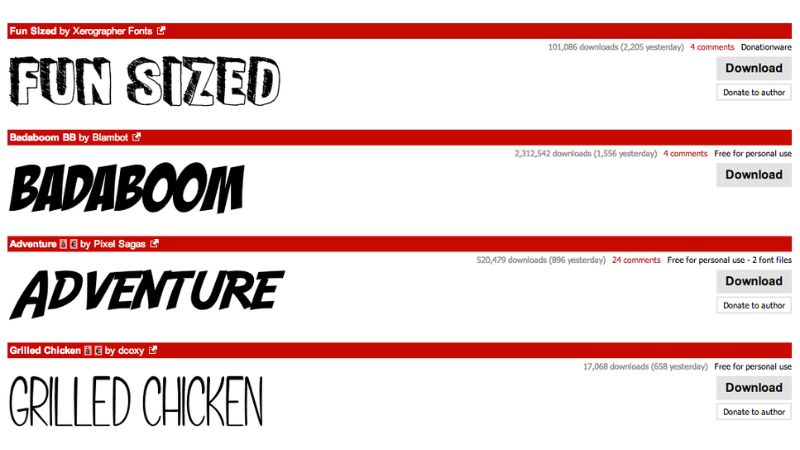
Trong thế giới của thiết kế và sáng tạo, font chữ không chỉ đơn thuần là những con chữ. Chúng là linh hồn của văn bản. Chúng có khả năng truyền tải cảm xúc, định hình phong cách và tạo ra một ấn tượng thị giác mạnh mẽ. Một font chữ được lựa chọn đúng đắn có thể biến một văn bản bình thường trở nên sang trọng. Nó cũng có thể làm cho một thiết kế trở nên vui nhộn hoặc chuyên nghiệp hơn. Tuy nhiên, việc tìm kiếm những font chữ đẹp và miễn phí không phải lúc nào cũng dễ dàng. Rất may mắn, có một “thiên đường” dành cho những người yêu thích font chữ. Đó chính là trang web DaFont. Bài viết này sẽ là một cẩm nang toàn diện. Chúng tôi sẽ hướng dẫn bạn mọi thứ về DaFont, từ cách tìm kiếm, tải về cho đến cài đặt và sử dụng.
DaFont là gì? Khám phá “Thiên đường” font chữ miễn phí
Trước khi bắt đầu tải về, việc hiểu rõ về font chữ và trang web DaFont sẽ giúp bạn có một cái nhìn tổng quan và sử dụng tài nguyên này hiệu quả hơn.
Font chữ là gì? “Trang phục” quyết định linh hồn của văn bản
Hãy tưởng tượng các con chữ giống như những người mẫu. Font chữ chính là những bộ trang phục mà họ khoác lên mình. Cùng một nội dung văn bản, nhưng với những font chữ khác nhau, nó sẽ mang lại những cảm giác hoàn toàn khác biệt. Một font chữ chân phương (serif) như Times New Roman sẽ tạo cảm giác trang trọng và cổ điển. Một font chữ không chân (sans-serif) như Arial lại mang đến sự hiện đại và rõ ràng. Một font chữ viết tay (script) có thể gợi lên sự mềm mại và lãng mạn. Việc lựa chọn font chữ chính là bạn đang lựa chọn “tính cách” cho thông điệp của mình. Nó là một yếu tố cực kỳ quan trọng trong thiết kế đồ họa, làm bài thuyết trình, hay đơn giản là tạo ra những tài liệu cá nhân độc đáo.
Giới thiệu DaFont: Kho tàng font chữ khổng lồ và đa dạng
DaFont là một trong những trang web lưu trữ và chia sẻ font chữ miễn phí lớn nhất và lâu đời nhất trên thế giới. Nó giống như một thư viện khổng lồ. Nơi đây, các nhà thiết kế font chữ từ khắp nơi trên thế giới có thể tải lên các tác phẩm của họ để chia sẻ với cộng đồng. Sức mạnh của DaFont nằm ở sự đa dạng không tưởng của nó. Trang web này chứa hàng chục ngàn font chữ khác nhau. Chúng được phân loại một cách cực kỳ chi tiết theo rất nhiều phong cách. Bạn có thể tìm thấy mọi thứ, từ những font chữ kinh dị cho một tấm poster Halloween, cho đến những font chữ thư pháp tinh tế cho một tấm thiệp cưới. Giao diện của trang web rất đơn giản và trực quan. Điều này giúp người dùng ở mọi trình độ đều có thể dễ dàng tìm kiếm và tải về những font chữ mà họ cần.
Làm quen với giao diện và các danh mục font chữ phổ biến
Giao diện của DaFont được thiết kế để bạn có thể tìm thấy thứ mình cần một cách nhanh nhất. Ở phía trên cùng là các hộp danh mục (categories) được phân loại theo chủ đề.
- Fancy (Cầu kỳ): Nơi chứa những font chữ trang trí độc đáo như Cartoon (hoạt hình), Western (cao bồi), Horror (kinh dị)…
- Foreign Look (Nét nước ngoài): Nơi bạn có thể tìm thấy các font chữ mô phỏng phong cách chữ viết của các quốc gia khác như Chinese (Trung Quốc), Japanese (Nhật Bản), Mexican (Mexico)…
- Techno (Công nghệ): Bao gồm các font chữ mang hơi hướng tương lai, khoa học viễn tưởng (Sci-fi), vuông vắn (Square)…
- Script (Viết tay): Danh mục cực kỳ phổ biến với các font chữ thư pháp (Calligraphy), chữ viết tay cá nhân (Handwritten)…
- Basic (Cơ bản): Nơi chứa các font chữ tiêu chuẩn như Serif và Sans Serif, phù hợp cho các văn bản dài. Việc dành thời gian khám phá các danh mục này sẽ giúp bạn tìm thấy rất nhiều “viên ngọc quý” ẩn giấu trên DaFont.
- Viết một bài blog cá nhân không kiếm tiền.
- Thiết kế một tấm thiệp mời sinh nhật cho bạn bè.
- Tạo một hình nền máy tính cho riêng mình.
Ngược lại, bạn không được phép sử dụng các font chữ này cho các dự án thương mại. Mục đích thương mại là bất kỳ dự án nào có thể giúp bạn hoặc công ty của bạn kiếm ra tiền. Ví dụ như thiết kế logo, làm bao bì sản phẩm, chạy quảng cáo, hay sử dụng trên một trang web kinh doanh.
Hướng dẫn tìm kiếm và sử dụng font “100% Free” cho mục đích thương mại
Nếu bạn cần một font chữ cho một dự án thương mại, DaFont vẫn có một giải pháp an toàn cho bạn.
- Bước 1: Truy cập vào một danh mục font chữ bất kỳ.
- Bước 2: Nhìn lên phía trên danh sách các font, bạn sẽ thấy một bộ lọc. Hãy nhấn vào nút “More options” (Thêm tùy chọn).
- Bước 3: Một vài ô trống sẽ hiện ra. Hãy tìm đến ô “100% Free” và đánh dấu tích vào đó.
- Bước 4: Nhấn vào nút “Submit” (Gửi). Bây giờ, trang web sẽ chỉ hiển thị những font chữ có giấy phép “100% Free”. Điều này có nghĩa là bạn có thể tự do sử dụng chúng cho cả mục đích cá nhân và thương mại mà không cần phải lo lắng. Đây là một bước cực kỳ quan trọng khi làm việc với DaFont.
Hướng dẫn chi tiết từ A-Z: Tải và cài đặt font từ DaFont
Sau khi đã hiểu rõ các quy tắc, bây giờ là lúc để bắt đầu quá trình tải và cài đặt.
Bước 1: Tìm kiếm và “ướm thử” font chữ với tính năng Preview
Một trong những tính năng mạnh mẽ nhất của DaFont là hộp xem trước (Preview).
- Bước 1: Tìm đến một danh mục font chữ bạn thích.
Kết luận
Qua bài viết chi tiết này, hy vọng bạn đã có một cái nhìn toàn diện và rõ ràng về DaFont. Đây thực sự là một nguồn tài nguyên vô giá cho bất kỳ ai yêu thích sự sáng tạo. Nó cung cấp một kho tàng font chữ khổng lồ và đa dạng, giúp bạn thể hiện cá tính và nâng tầm các sản phẩm thiết kế của mình. Tuy nhiên, hãy luôn là một người dùng thông thái. Hãy luôn chú ý đến giấy phép sử dụng để đảm bảo bạn không vi phạm bản quyền của tác giả. Quá trình tải và cài đặt font chữ hoàn toàn không hề phức tạp. Với những hướng dẫn chi tiết trong bài viết, bạn hoàn toàn có thể tự mình làm chủ công cụ này.